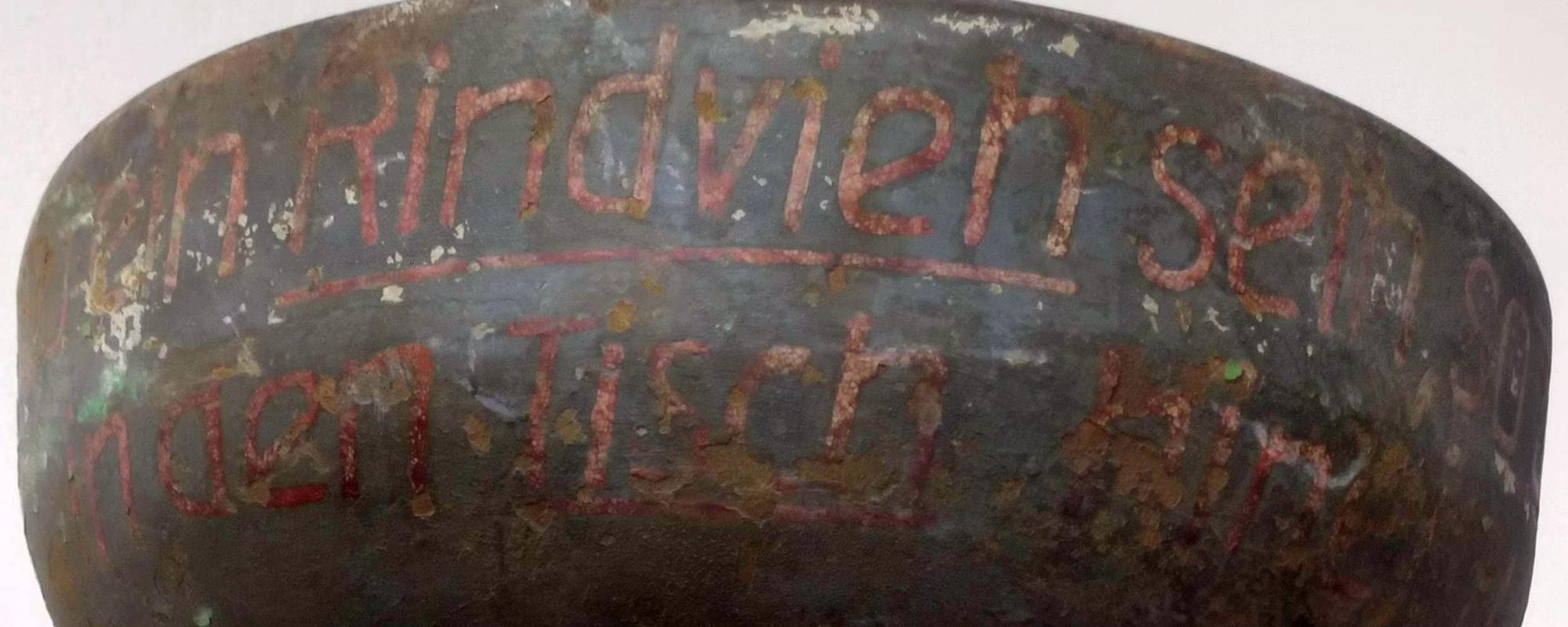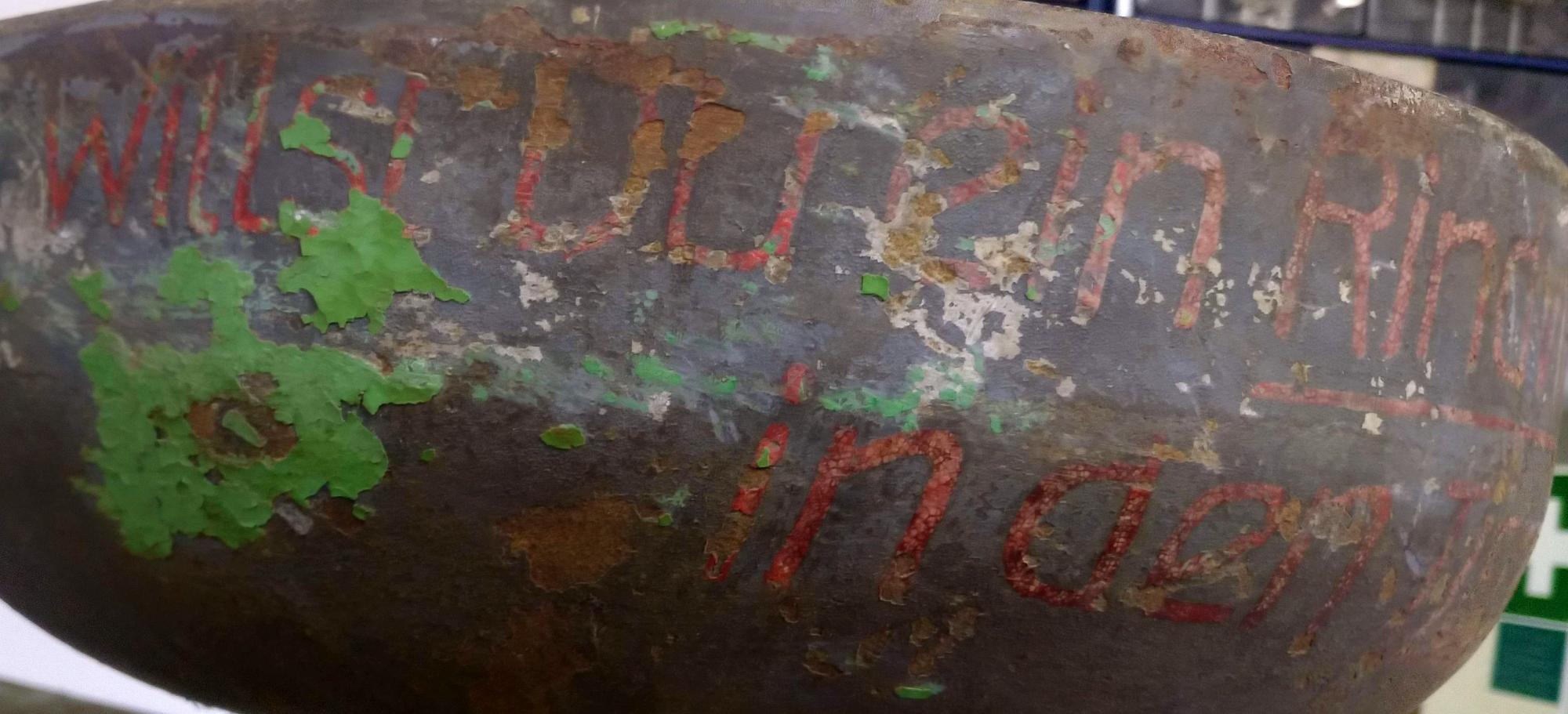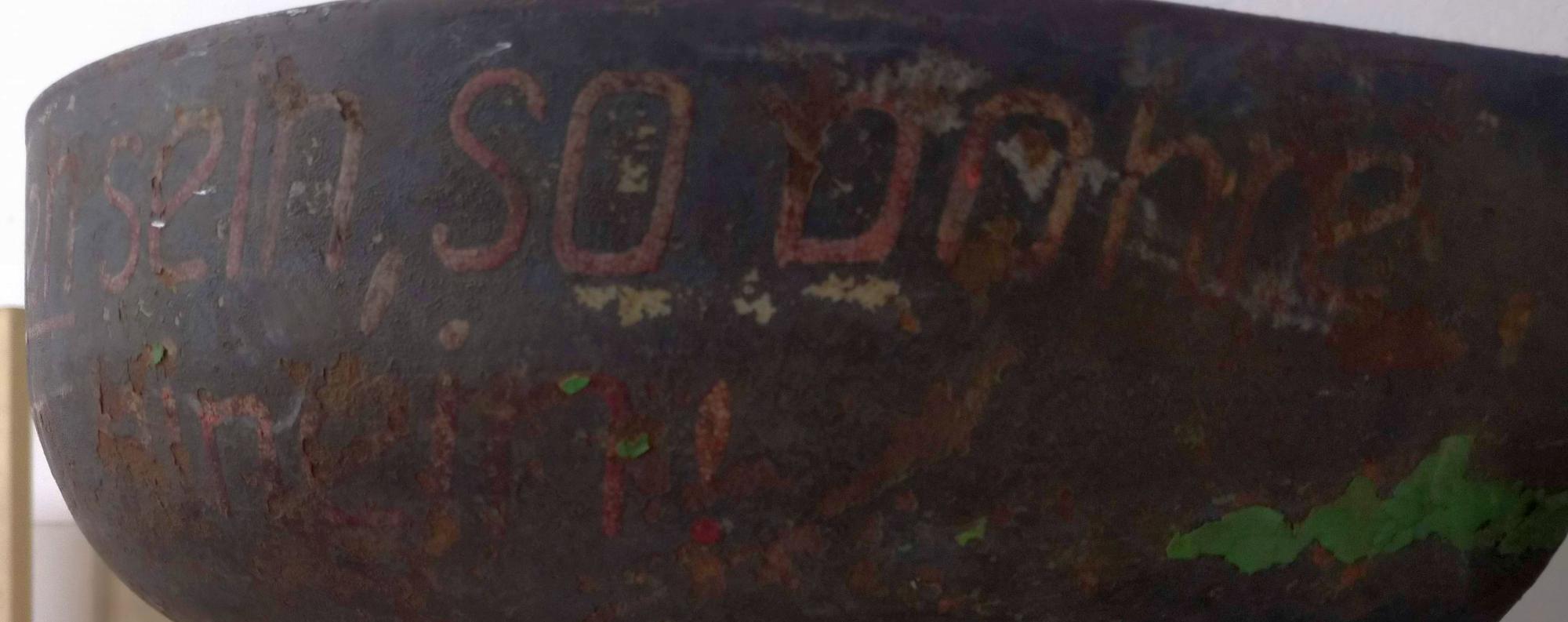
Welche Schriftart kommt der auf meiner 80 Jahre alten Bohrmaschine am nächsten
Ich habe eine alte Flott 603 Bohrmaschine Baujahr 1939 restauriert.
Auf der oberen Riemenabdeckung hat jemand einen Spruch aufgemalt - den möchte ich plotten und wieder neu aufbringen.
Etwas Hilfe würde mich da echt weiterbringen
Es dürfte ja handgeschrieben sein. Warum nicht wieder so machen? Ein Font wird den Charme der Handarbeit nie nahekommen. Man könnte es mit Transparenzpapier nachzeichnen und dann bereinigen. Am besten in einem vektorbasierten Grafikprogramm, wo man nur das Skelett zeichnet und der hinreichend breite Strich mit abgerundeten Strichenden dann um dieses Skelett gelegt wird.
Das denke ich auch.
Aber auch das Plotten und mit gleichmäßig ebener Folie auftragen passt auch nicht zum Charme. In der Restaurierung steckt bestimmt viel Handarbeit – warum nicht den letzten Schritt genauso :-?
Soll die Abdeckung denn neu lackiert werden?
Dann würde ich vorher, wie Ralf schon schrieb, das Skelett mit Transparentpapier abzeichnen und nachher übertragen. Mit einem vernünftigen Pinsel kriegt man das dann nachgemalt. Fände ich authentischer …
Ihr habt vollkommen recht - Handbeschriftet wäre das authentischste.
Ich kann zwar super Maschinen reparieren aber Zeichnen und artverwandtes ist mir leider nicht gegeben.
Ein Kollege hatte voller Zuversicht versprochen das sei kein Problem - wars leider dann doch.
Jetzt ist das Teil lackiert, nur die Bilder sind über.
Das macht das ganze konkret aber nicht einfacher 🤔
Bei Jeff Levine habe ich ein paar ähnliche Schriften gefunden, aber die die formell gut passen würden haben leider keine Gemeinen:
Andererseits, diese kommt schon dem Ganzen recht nah, und warum nicht alles im Versalsatz :-?
Original bekommst du es eh nicht mehr.
Wobei ich das Original auch nicht als so künstlerisch herausragend bewerten würde, als dass man es nicht relativ leicht mit Pinsel nachgeahmt bekommt.